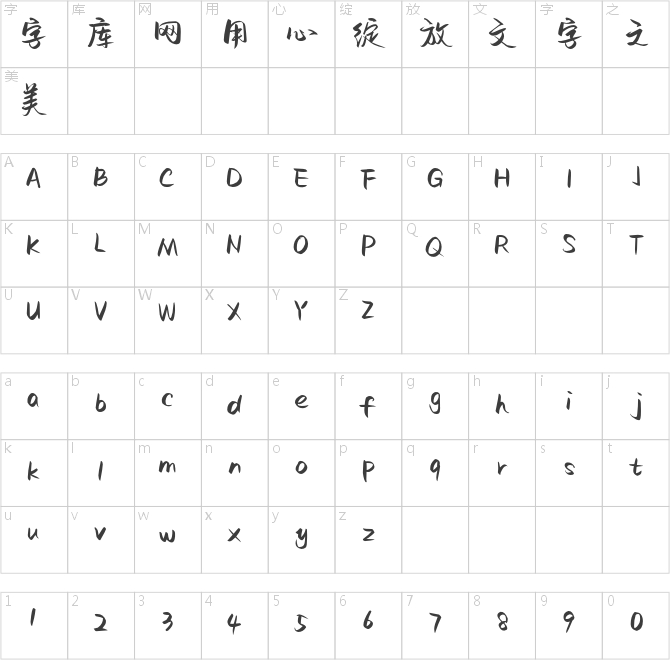
造字工房瑜悅體 詳情頁
字體名稱: 造字工房瑜悅體
造字工房瑜悅體
造字工房瑜悅體,用筆剛勁中含秀潤,圓厚中見鋒利,行字疏密曲直,縱橫跌宕,筆勢連綿飛動,一氣呵成。其字結(jié)體勁媚,平穩(wěn)生動;整體風(fēng)格連貫呼應(yīng),有顧盼情生之意態(tài)。適用于大標(biāo)題及個性品牌設(shè)計推廣等環(huán)境。本字體為簡體字庫,采用OpenType/CID格式,Adobe-GB1-5編碼?;谥腥A人民共和國GB2312-80字符集標(biāo)準(zhǔn),另按需添加101個漢字。共收容字?jǐn)?shù)6864CJK漢字,ASCII常用字符100個。